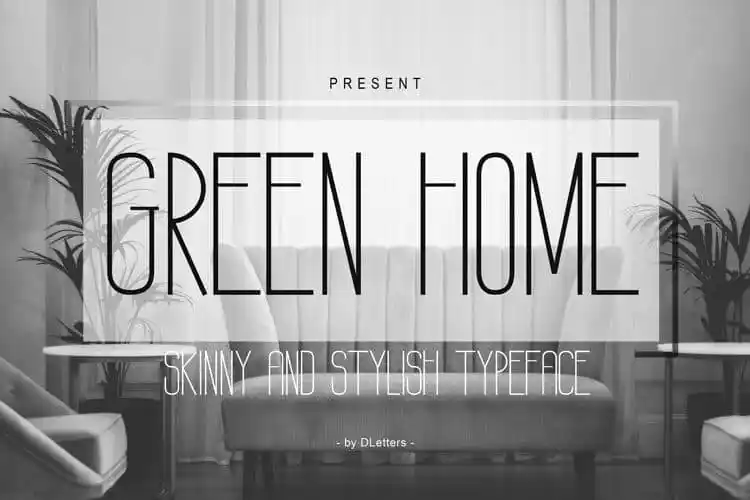
A fonte ‘GREEN HOME Sans Serif Font’ é uma escolha perfeita para quem busca combinar elegância com modernidade na sua marca ou logomarca. Feita pelo designer DLetters Std, esta font está disponível como uma opção de letra fácil e versátil, ideal tanto para designers mais experientes quanto para iniciantes que buscam novas maneiras de apresentar seu trabalho. A ‘GREEN HOME Sans Serif Font’ tem um design clean e sofisticado, perfeito para trabalhos relacionados ao tema da decoração de casa ou criações artísticas com fotografias. Ideal tanto para uso nas plataformas digitais como no Canva quanto em qualquer outro software, esta fonte não requer a utilização de recursos OpenType, tornando-a uma opção confiável. Seu design elegante e minimalista se adequa perfeitamente à temática Home Decorating ou Home Idea, sendo também perfeita para complementar trabalhos de fotografia e criações artísticas. Perfect para designers buscando incorporar um elemento personalizado e sofisticado em seus projetos, sem precisar investir na complexidade adicional do OpenType.